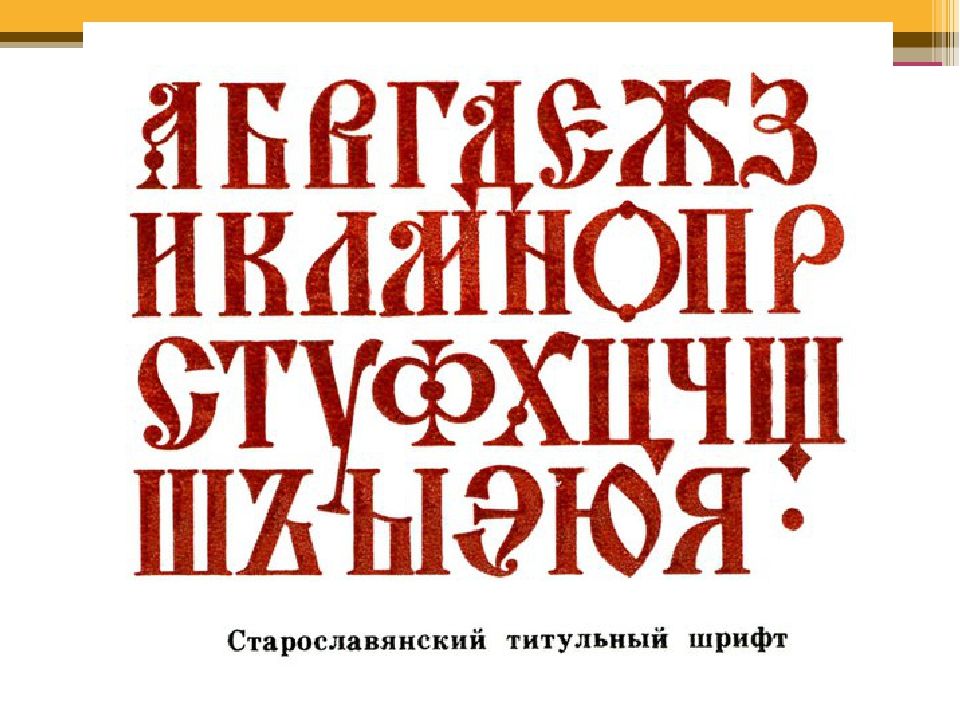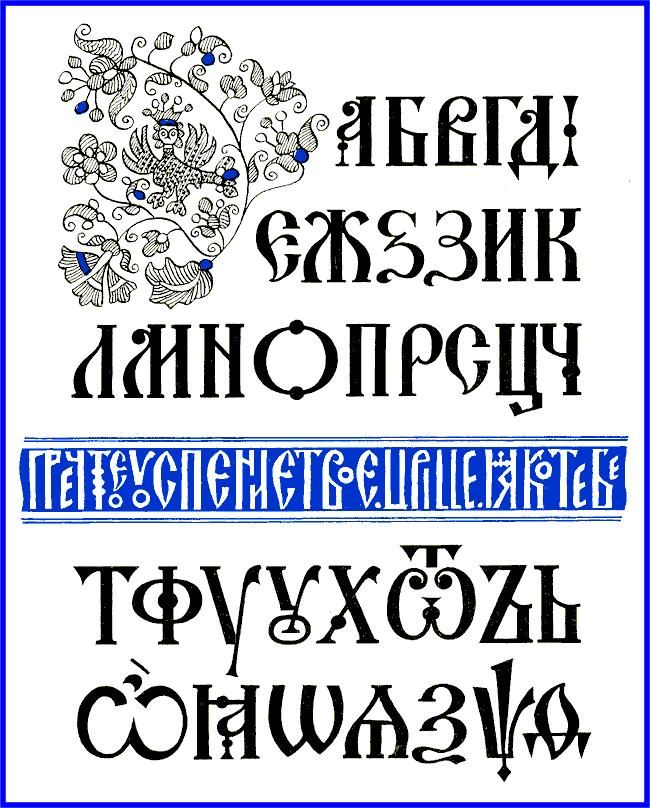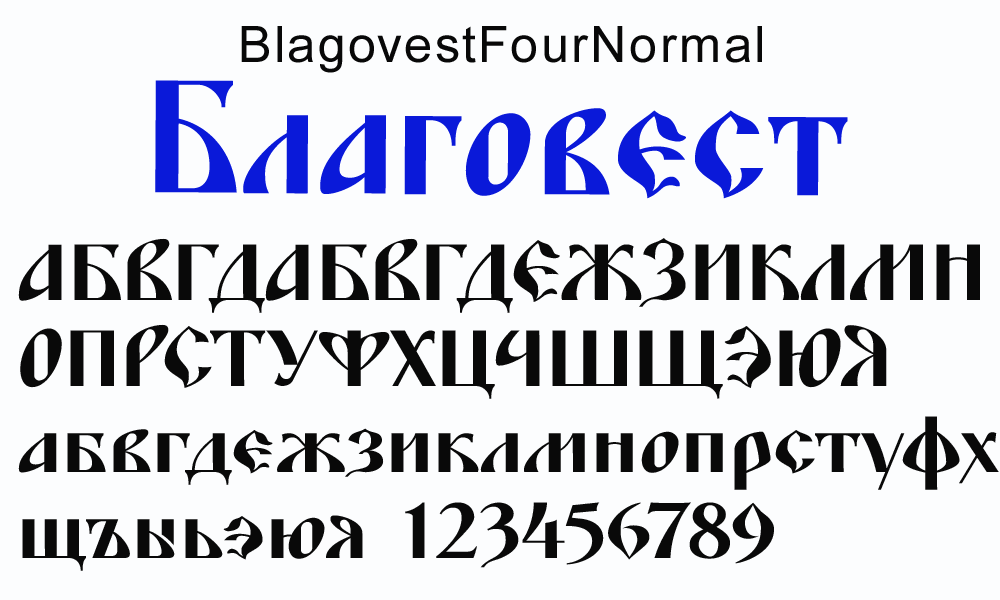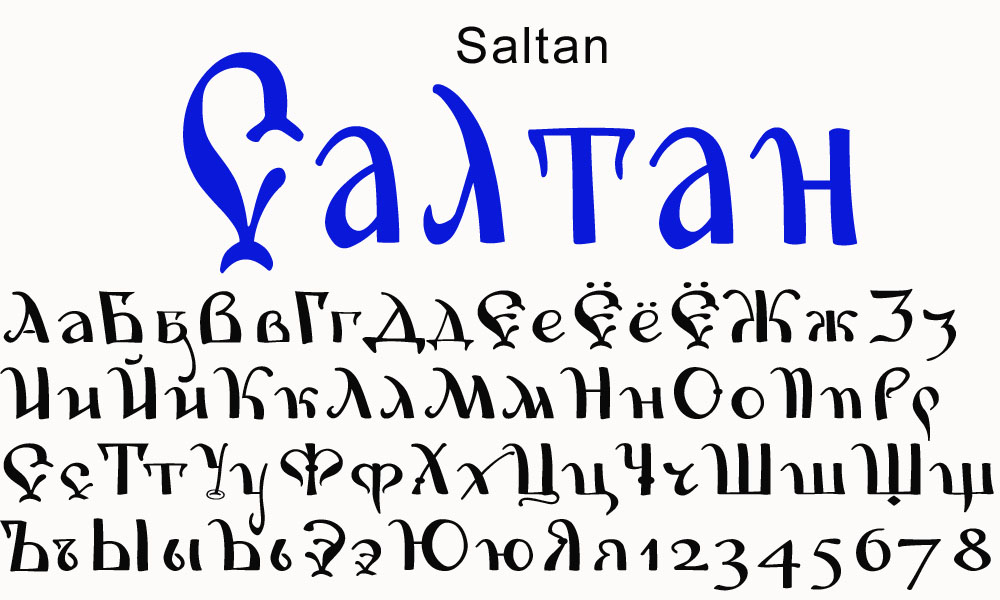
caption id=attachment_8099 align=alignnone width=600] Пример использования шрифта CyrilicOld. Старославянский.
UCS-шрифт сделан на основе старой, 13-шрифтовой коллекции Irmologion. работающий в Word 95-97 и PageMaker, и работающий в Word 97-2000.
Для старославянского языка у нас есть шрифт Kirillica Wincyr (смотрите изображение. Для Word 97, для других современных программ Unicode и для.
Об истории создания современной версии азбуки и пр. см. Кириллица. Старославянская. С введением книгопечатания в XV XVI веках печатный шрифт был отлит по образцу позднего младшего полуустава. Поздний полуустав.
Там же доступны шрифты Theano (вариации на тему греческого) и Monomachus (качественный шрифт для старославянских текстов). Мне неизвестно.
И кто бы такой файл ни открыл, при наличии шрифта с поддержкой нужного диапазона, он узрит. Церковно-славянский текст, кудряво набранный одним шрифтом, при переключении на другой шрифт.
Выпущен новый церковнославянский шрифт Kathisma / Новости / Патриархия.ru
Сообществом славянской типографики выпущен новый церковнославянский шрифт Kathisma. Kathisma — декоративный, хорошо подходящий для оформления заголовков шрифт, повторяющий часто используемую в изданиях XVIII-XX вв. гарнитуру; похож на довольно распространенный коммерческий шрифт Psaltyr.
Основные результаты деятельности Сообщества: стандарт инвариантного представления славянских текстов (HIP), конвертеры и средства верстки в TeX на его основе; освоение технологии OCR для оцифровки текстов с диакритикой и создание с ее помощью практически полного корпуса богослужебных и библейских церковнославянских текстов; разработка стандарта-кодировки UCS8 и шрифтов на ее основе, создание пакета «Ирмологий» для набора и редактирования текстов в кодировке UCS8 (под MS Word) и др.
Так что «Глава 1» теперь будет печататься как «Глава 1», «Справочники».